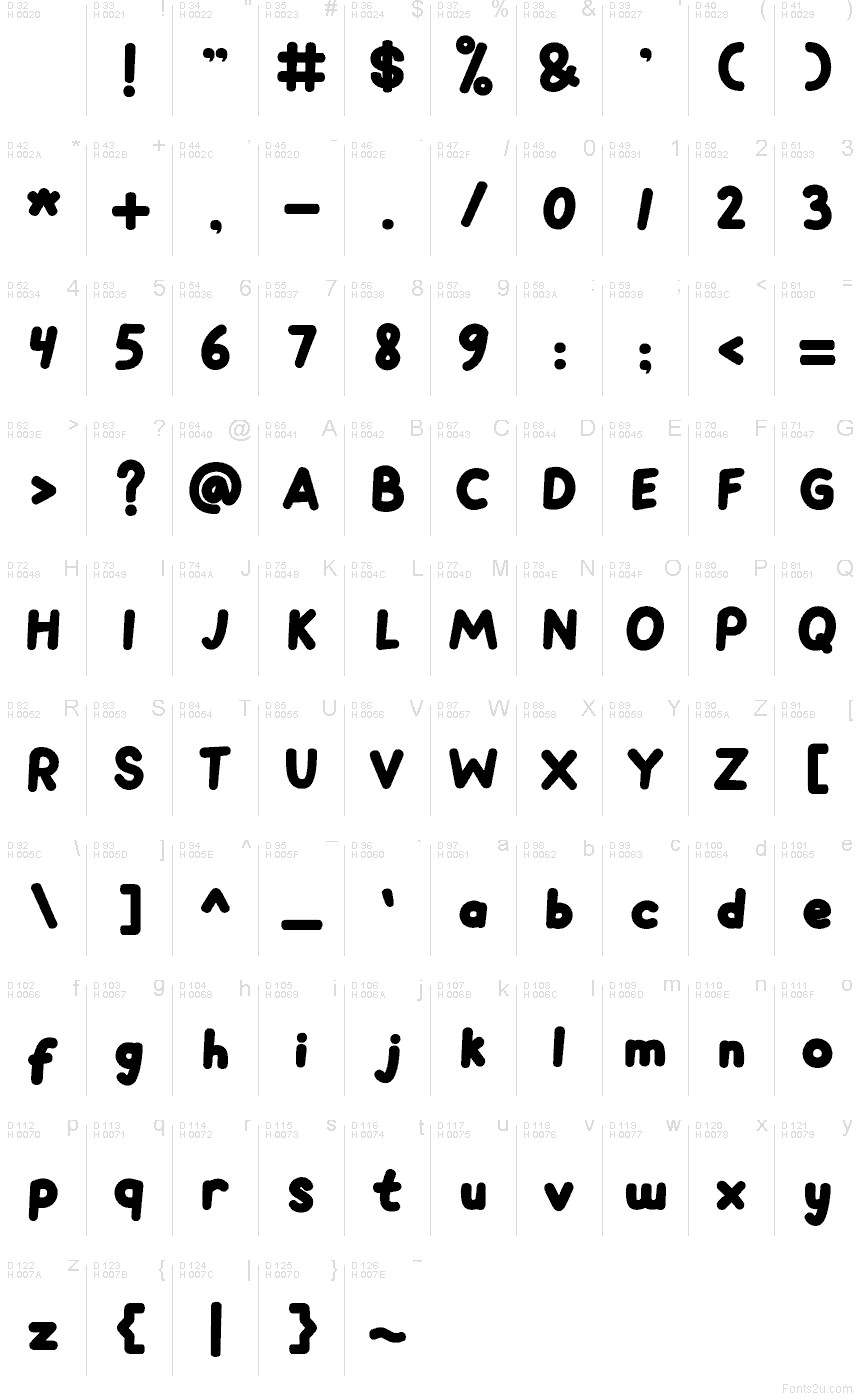
Fitory di Tokokoo è un carattere display in stile cartoon gratuito, con lettere morbide, piene e un ritmo vivace. Le forme arrotondate risultano accoglienti e amichevoli; grazie ai tratti spessi, alle curve strette e al ritmo leggermente irregolare, il lettering appare tutto fuorché rigido.
È perfetto per il branding rivolto ai bambini, il packaging di snack, titoli di poster allegri, miniature di YouTube, sticker design e brevi intestazioni per app o giochi dove serve un carattere gratuito dal tono brillante e spensierato. Poiché le lettere sono molto corpose e compatte, Fitory dà il meglio di sé in contesti brevi come copertine o titoli, dove la sua silhouette evidente comunica il messaggio in un attimo.